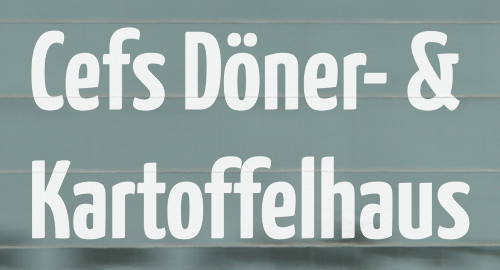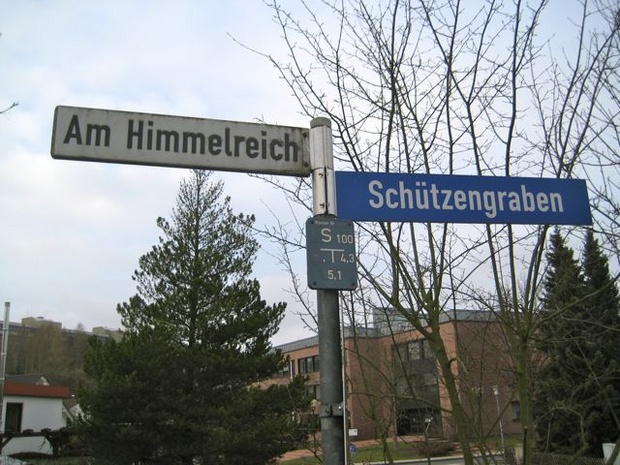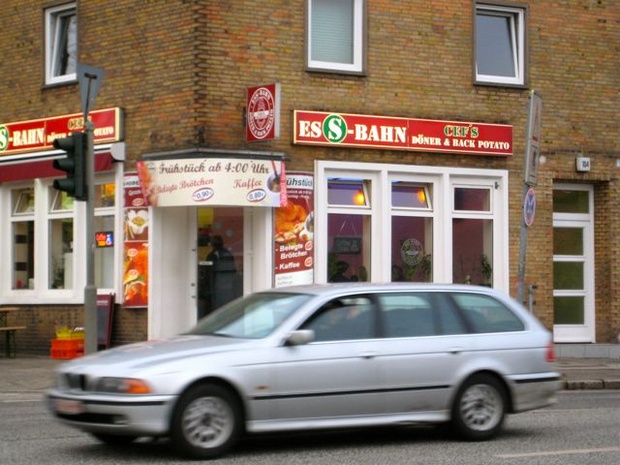
Typostreifzug durch die Stadt ...
Ich war mal wieder spazieren …
Mit der Schrift geht wirklich alles … Hamburger Abendblatt, Wochenendausgabe:
Mit der Schrift geht wirklich alles … Hamburger Abendblatt, Wochenendausgabe: …
Eine Mobilnummer als "Kondolenzkontakt" ist ja noch besser als eine Kontonummer … soll man eine SMS schreiben? Eine MMS?
Ich kann nur mutmaßen. Es greift ja um sich, dass Einbrecher solche Anzeigen lesen und gezielt Trauerhaushalte während der Beerdigung ausrauben. Vielleicht wollte da jemand auf Nummer sicher gehen und keinerlei Kontaktdaten angeben, die Rückschlüsse auf die Adresse zulassen.
Das mag sein … in dem Fall wäre das aber egal, da es laut Telefonbuch nur genau einen Dr. Gert Spoerl in Deutschland gab ;-)
Aber wahrscheinlich haben sich die Hinterbliebenen gedacht Er selbst kann ja nicht mehr ans Telefon gehen … also ist es irgendwie auch wieder verständlich.
Du Fuchs! ;-)
Bin grad selbst erschrocken mit was man sich so beschäftigt … :shock:
Freud und Leid liegen manchmal dicht beieinander:
Aus zwei mach eins:
Fremdsprachenakrobat am Werk:
Wo kann ich Cef für das Bundesverdienstkreuz vorschlagen? Immerhin ist seine Integration vorbildlich – er schreibt genau wie die Deutschen. Seine Anwendung des Genitivapostrophs™, des Kopplungsleerzeichens™ und der kosmopolitischen »Rückenkartoffel« unterscheidet sich durch nichts von abertausenden urdeutschen Geschäften. In Anatolien würde man solche Sprache hingegen vergeblich suchen. Koch und Sarrazin wären stolz auf Cef!
Davon ganz abgesehen ist die ES(S)-BAHN toll!
finde ich schon etwas angemessen. dadurch ist die buchstabensammlung als name gekennzeichnet. ich würde mich sonst stets fragen, was denn cefs wäre...
Das ist ja eine charmante Logoidee, aber was ist denn mit der Unterzeile passiert?
Und das Wort »Klasse« klebt dem Herrn ganz schön im Nacken …
[Den Genitivapostroph] finde ich schon etwas angemessen. dadurch ist die buchstabensammlung als name gekennzeichnet. ich würde mich sonst stets fragen, was denn cefs wäre...
Deswegen habe ich ja einen nicht negativ besetzten Begriff gewählt und bewusst nichts von einem Deppena… geschrieben. :baeh:
Hier macht ein Caterer mit »Die neue Ess-Klasse« Werbung.
Auch nicht übel. Ich meinte aber den Bezug zur offensichtlich nah gelegenen S-Bahn, incl. grünem Kreishintergrunds.
Dieser Cef bringt mein ganzes Weltbild ins Wackeln. Ohne Genitiv-Akzent wüßte ich auch nicht, daß das ein Name ist. :-o
Diesen Beitrag sollten wir ausschneiden, rot umranden und einrahmen.
Dass ich so etwas mal von Joshua lesen würde! *staun*
Aber Spaß beiseite, meint ihr nicht, dass man das Problem auch ohne Apostroph entschärfen könnte, wenn man auf Versalsatz verzichtete und alles grammatisch korrekt schriebe, ohne dass »Cefs« allein auf einer Zeile steht?